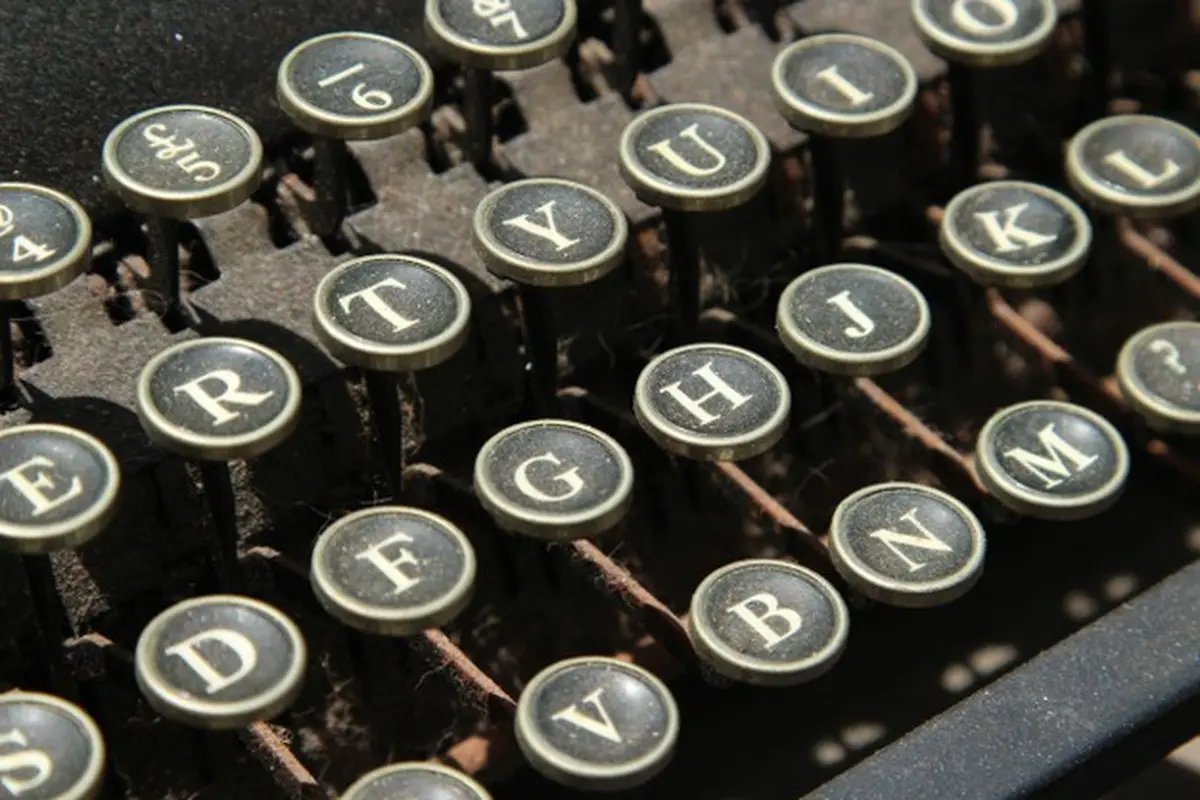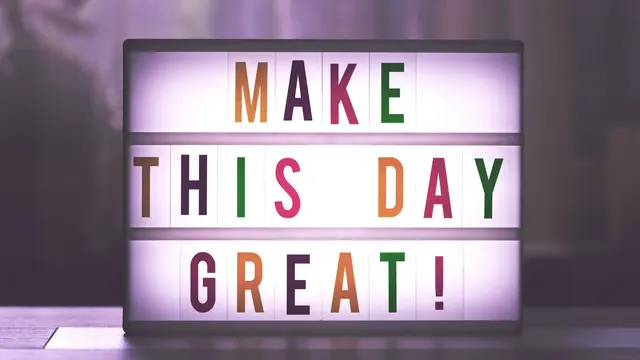
Liputan6.com, Jakarta Macam font punya beragam bentuk dan karakteristik. Font adalah sekumpulan karakter teks yang dapat ditampilkan dalam gaya dan ukuran tertentu. Mengenali macam font merupakan dasar penting dalam belajar tipografi.
Tipografi dalah seni mengatur huruf dan teks dengan cara yang membuat salinan terbaca, jelas, dan menarik secara visual bagi pembaca. Tipografi melibatkan macam font, tampilan, dan struktur, yang bertujuan untuk memperoleh emosi tertentu dan menyampaikan pesan tertentu. Dengan mengetahui macam font, tipografi dapat dibuat dengan benar.
Macam font secara mendasar terbagi dalam empat tipe. Ini meliputi serif, sans serif, script, dan decorative. Dari empat tipe ini ada banyak macam font yang bisa ditemukan. Berikut macam font yang perlu dikenali, dirangkum Liputan6.com dari berbagai sumber, Senin(14/06/2021).
Macam font: serif
Serif adalah macam font yang memiliki ciri khas berupa garis kecil atau stroke secara teratur melekat pada ujung huruf. Dalam tipografi, serif adalah goresan ekstra kecil yang ditemukan di akhir goresan vertikal dan horizontal utama dari beberapa huruf. Istilah "font serif" mengacu pada gaya jenis apa pun yang memiliki serif.
Font serif sangat populer dan telah ada selama bertahun-tahun. Times Roman adalah salah satu contoh font serif. Font dengan serif sangat berguna untuk blok teks yang besar. Serif memudahkan mata untuk menelusuri teks. Sebagian besar buku, surat kabar, dan majalah menggunakan font serif untuk keterbacaannya. Font serif tidak begitu berguna untuk desain web, terutama jika digunakan dalam ukuran kecil. Karena resolusi layar beberapa monitor komputer rendah, serif kecil dapat hilang atau kabur, yang membuat teks sulit dibaca.
Jenis font serif
Font serif memiliki beragam jenis dengan gayanya sendiri. Berikut jenis font serif:
Old Style
Kategori ini mencakup tipe Romawi pertama, yang awalnya dibuat antara akhir abad ke-15 dan pertengahan abad ke-18, serta tipografi yang berpola setelah yang dirancang pada periode sebelumnya. Serif hampir selalu dikurung dalam desain gaya lama dan serif kepala sering miring. Beberapa versi, seperti desain gaya lama Venesia sebelumnya, dibedakan oleh goresan silang diagonal dari huruf kecil e. Contoh macam font old serif adalah Arno, Bookery, Callisto MT, dan Centaur.
Transitional
Tipografi ini mewakili transisi antara gaya lama dan desain neoklasik, dan menggabungkan beberapa karakteristik masing-masing. Macam font ini berada di antara font "gaya lama" dan "modern", sehingga dinamakan "transisi". Perbedaan antara garis tebal dan tipis lebih menonjol daripada di gaya lama, tetapi kurang dramatis dibandingkan dengan font Didone yang mengikutinya. Contoh dari font serif transisi adalah Baskerville, Times New Roman, Century, Pepertua, dan Cambria.
Neoclassical & Didone
Jenis font serif ini sering juga disebut serif modern. Font ini mencolok untuk digunakan sebagai headline atau judul. Font serif Neoclassical & Didone juga kerap digunakan sebagai logo. Font ini sulit dibaca daripada gaya tipe sebelumnya dan yang lebih baru yang dikembangkan untuk teks. Namun, mereka lebih khas daripada font transisi yang mendahuluinya. Contoh dari font serif Neoclassical & Didone adalah Bodoni, Didot, Bernhard Modern Roman, dan Aster.
Slab
Serif Tipografi slab serif menjadi populer pada abad ke-19 untuk tampilan iklan. Tipografi ini memiliki serif yang sangat berat dengan sedikit atau tanpa tanda kurung. Umumnya, perubahan berat stroke tidak terlihat. Bagi banyak pembaca, gaya tipe slab serif terlihat seperti desain sans serif dengan tambahan sederhana serif berat (berat stroke). Contoh dari slab serif adalah Memphis, Rockwell, Courier, dan Roboto.
Macam font: sans serif
:strip_icc():format(webp)/kly-media-production/medias/3481620/original/001131000_1623645558-pexels-photo-2255441.jpeg)
Dalam tipografi, sans serif merupakan macam font yang tidak memiliki fitur perluasan yang disebut "serif" di akhir goresan. Font sans-serif cenderung memiliki variasi lebar goresan yang lebih sedikit daripada font serif. Mereka sering digunakan untuk menyampaikan kesederhanaan dan modernitas atau minimalis.
Font sans-serif telah menjadi yang paling umum untuk tampilan teks di layar komputer. Pada tampilan digital beresolusi lebih rendah, detail halus seperti serif mungkin hilang atau tampak terlalu besar. Ini membuat font sans serif lebih mudah dibaca pada tampilan digital.
Jenis font sans serif
Grotesque Sans Serif
Ini adalah tipografi sans serif pertama yang populer secara komersial. Kontras dalam bobot goresan paling terlihat dalam gaya ini. Dari pandangan luas, grotesque digunakan sebagai sinonim untuk font sans serif pada umumnya. Lebih khusus lagi, grotesque mengacu pada kumpulan font sans serif yang diproduksi sekitar tahun 1815. Contoh dari font ini adalah Austria, Bell Gothic, Geneva, Monotype Grotesque, dan News Gothic.